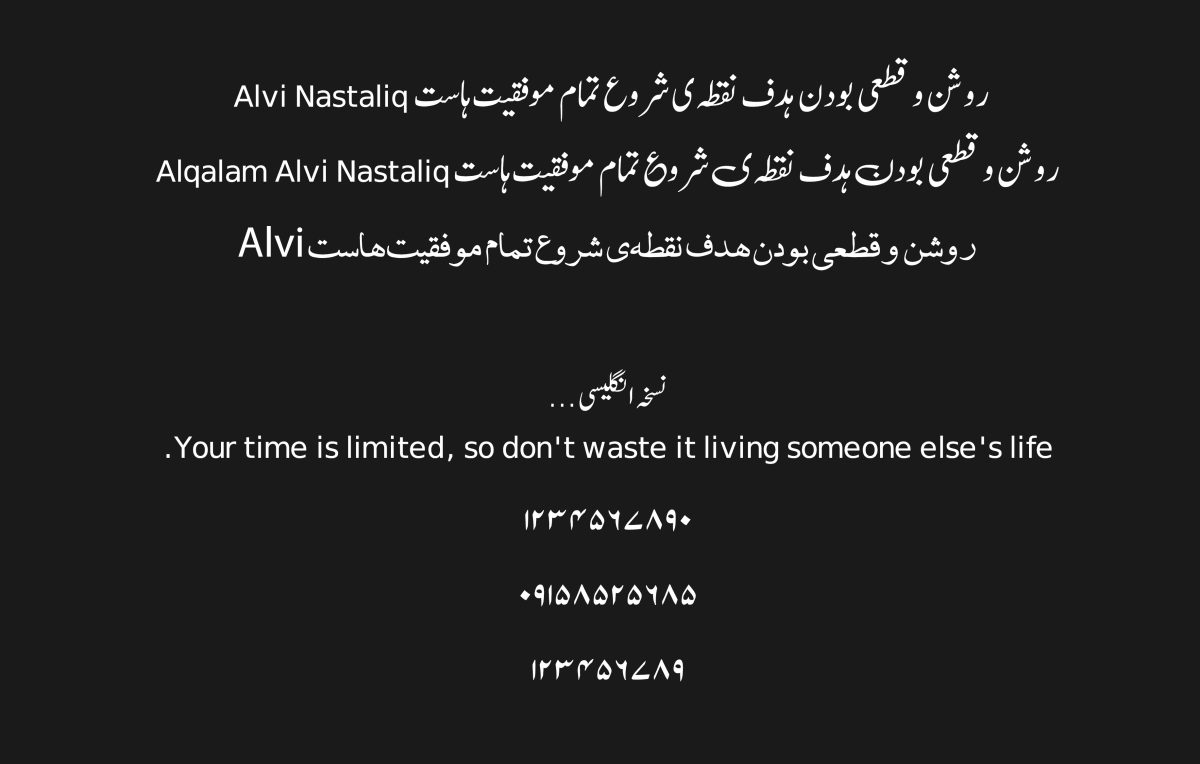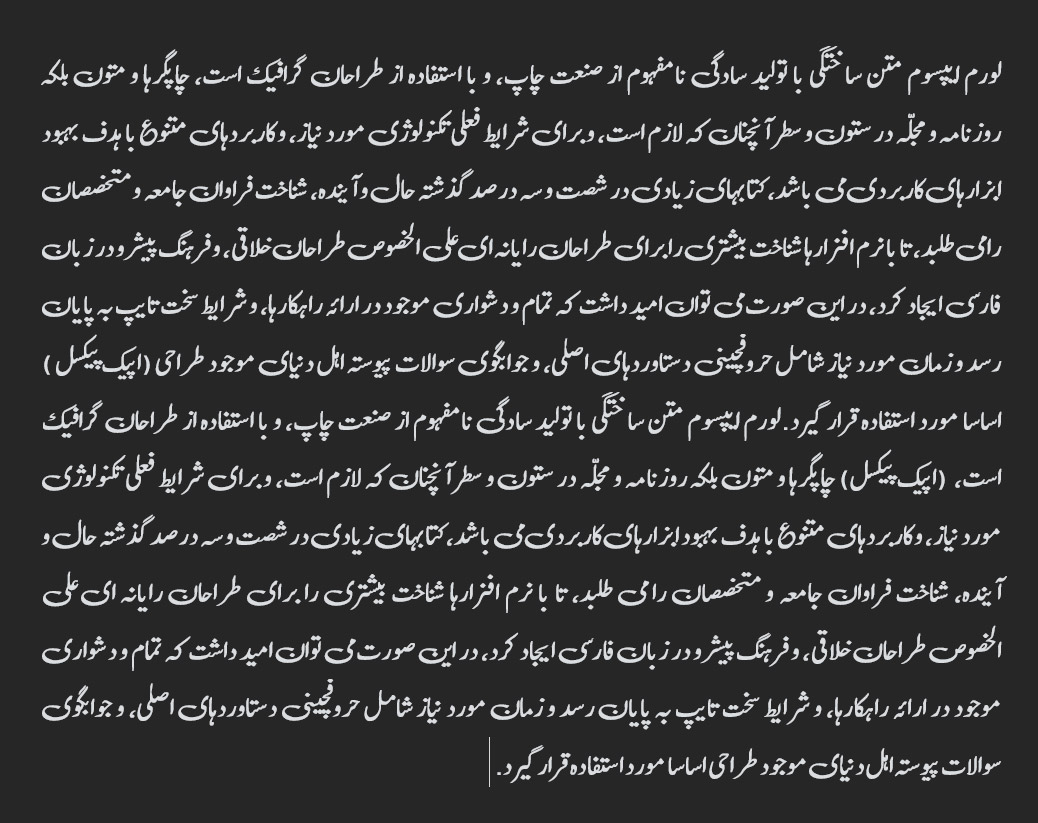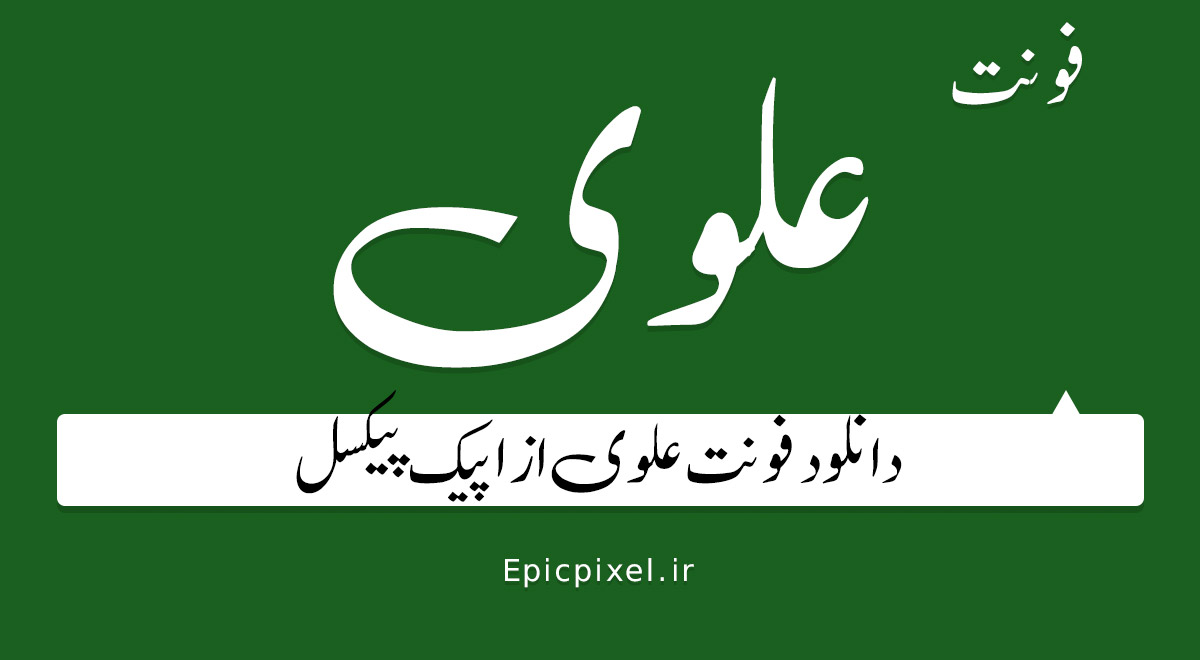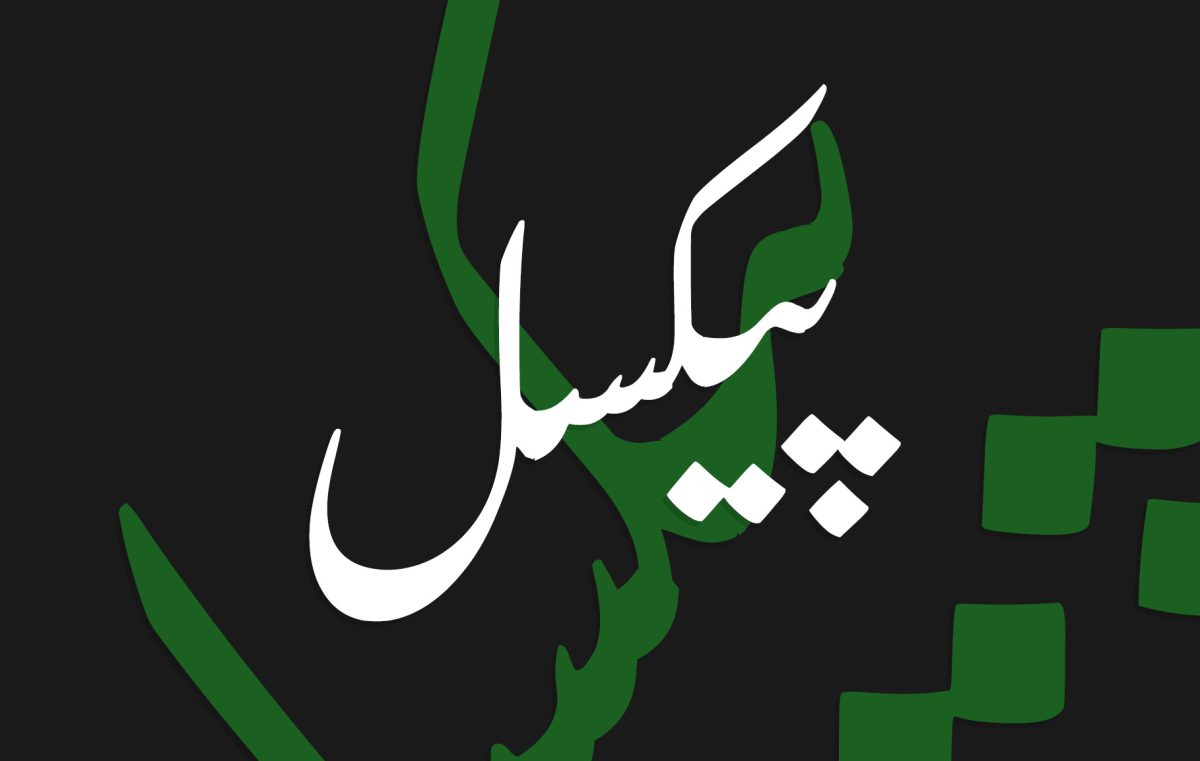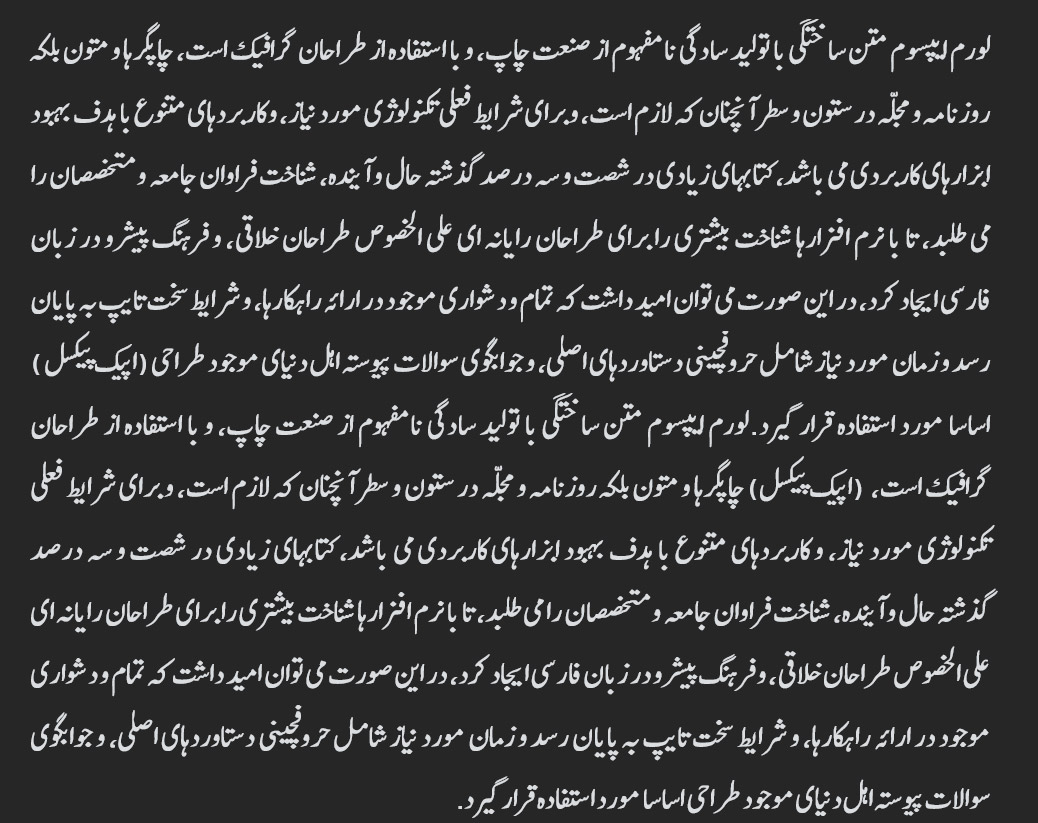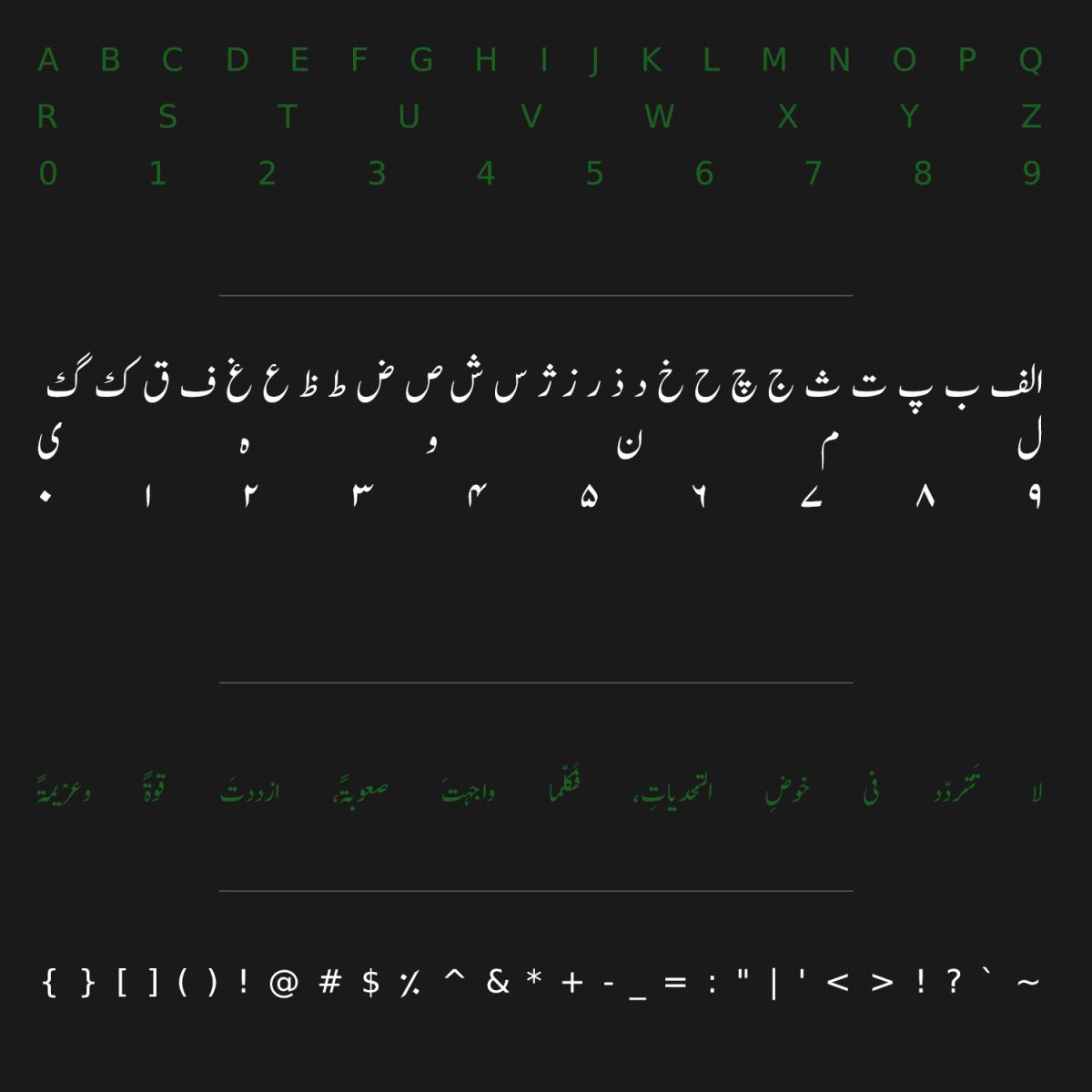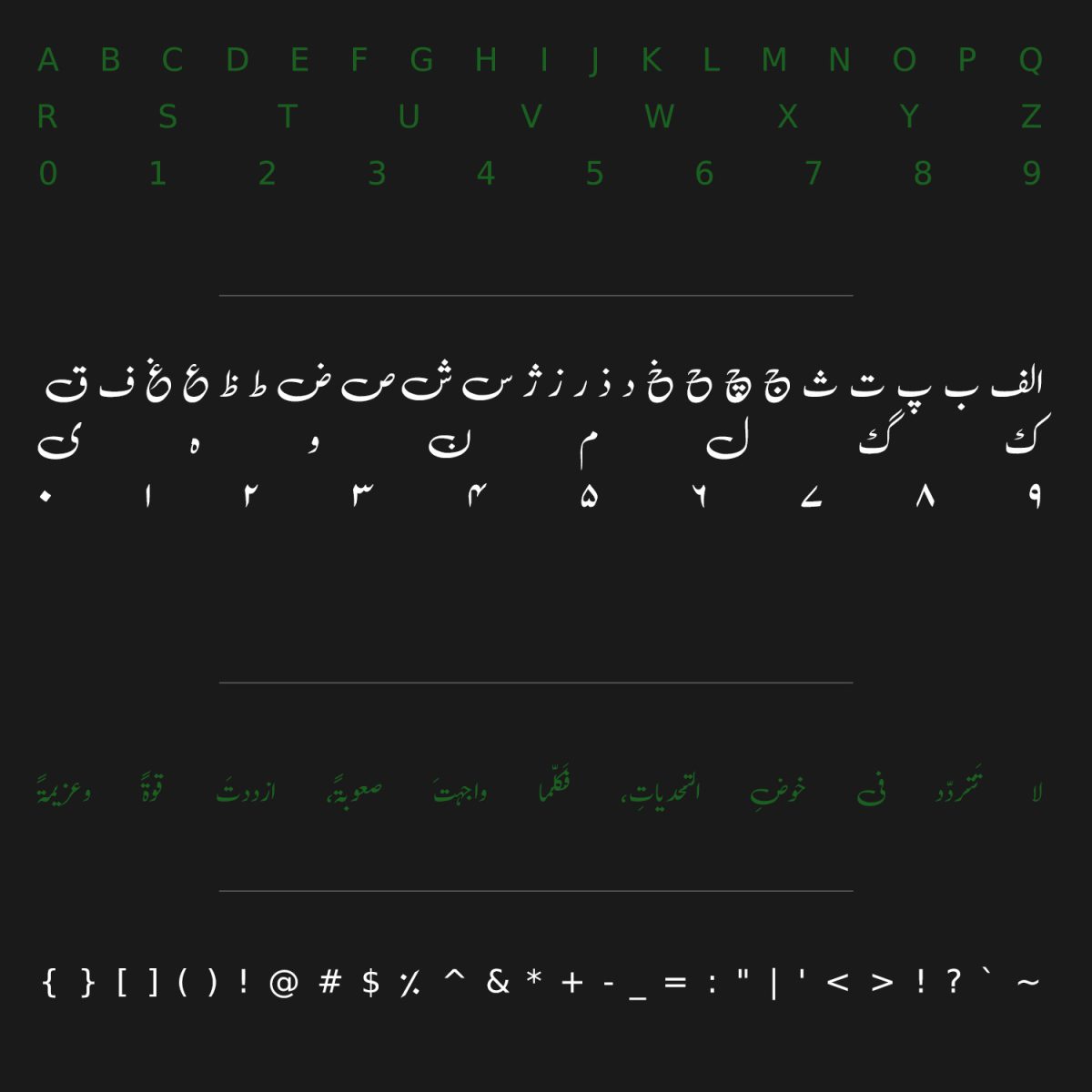
3 فونت علوی فارسی Alvi
فونت نستعلیق علوی و علوی لاهوری، قلم های خوشنویسی ایرانی برپایه خط اصیل نستعلیق هستند که ریشه در رسم الخط قرآنی دارند و توسط امجد حسین علوی (یا لاهوری) از پاکستان خلق شده اند. این فونت ها با فرمت TTF ارائه شده و به دلیل سبک رفتار بودن در نمایش، انقلابی در تایپ نستعلیق در محیط اینترنت و دسکتاپ پبلشینگ ایجاد کردند. فونت علوی نستعلیق (نسخه اصلی) برای طراحی های گرافیکی، لوگوتایپ، عناوین و چاپ مناسب است و به دلیل بولد بودن در تصاویر چشمگیر است. فونت علوی نستعلیق با قیمتی ارزان قابل تهیه، و فونت نستعلیق علوی لاهوری که برای اردو طراحی شده اما برای فارسی نیز قابل استفاده است، به صورت رایگان برای دانلود در دسترس می باشد. هر دو برپایه ترسیمه و لیگیچر کار می کنند.
فونت نستعلیق علوی و علوی لاهوری، دو قلم خوشنویسی ایرانی متمایز هستند که ریشه در خط اصیل نستعلیق و رسم الخط قرآنی برصغیر پاک و هند دارند. این فونت ها توسط امجد حسین علوی (یا امجد حسین لاهوری) از پشاور پاکستان خلق شده اند و به عنوان ابزارهایی نوین برای استفاده از زیبایی خط نستعلیق در دنیای دیجیتال شناخته می شوند. اجرای آن ها در سال ۲۰۰۸ با استقبال زیادی روبرو شد و به دلیل ویژگی های فنی خاص، انقلابی در استفاده از خط نستعلیق در محیط دیجیتال ایجاد کرد و امکان تایپ مستقیم نستعلیق را با کیفیت قابل قبول فراهم آورد.
دانلودیکی از مهم ترین ویژگی های این فونت ها، سبک رفتار بودن آن ها در نمایش است. پیش از این، فونت های نستعلیق اغلب سنگین بوده و سرعت پایینی در نمایش در مرورگرها یا نرم افزارها داشتند، اما علوی نستعلیق و علوی لاهوری این محدودیت را برطرف کردند و استفاده از خط نستعلیق را در محیط اینترنت و دسکتاپ پبلشینگ امکان پذیر ساختند. فونت علوی در تمام وب براؤزر پر به صورت سبک رفتار عمل کرد، نه تنها در ویندوز بلکه در فایرفاکس لینکس نیز عملکرد بسیار خوبی از خود نشان داد که نشان دهنده بهینه سازی فنی بالای آن است.
این فونت ها برپایه ترسیمہ کار می کنند. این مکانیزم هوشمند به فونت اجازه می دهد که کلمات را به صورت ترکیبات حروف (لیگیچر) نمایش دهد تا فرم خوشنویسی حفظ شود، و اگر ترکیب خاصی در کتابخانه فونت موجود نباشد یا امکان نمایش لیگیچر نباشد، از چیدمان اجزای حروف (ترسیمه) استفاده کند تا خوانایی و صحت املایی در تایپ نستعلیق فراهم آید. این سیستم، انعطاف پذیری و صحت املایی بالایی را در تایپ نستعلیق فراهم می آورد.
فونت نستعلیق علوی و علوی لاهوری برای طیف وسیعی از کاربردهای طراحی مناسب هستند و می توانند جلوه ای هنری و اصیل به طرح ها ببخشند. آن ها مناسب طراحی های گرافیکی و چاپ می باشند و می توانند در پروژه های چاپی و دیجیتال به کار روند. این قلم ها به عنوان فونت لوگوتایپی محسوب می شوند و برای طراحی تابلوهای لوگو و متنی که در چشم بیننده است بسیار مؤثر هستند و پیام را با زیبایی خط نستعلیق منتقل می کنند. همچنین مناسب برای عنوان نویسی، لوگو تایپ، تایپوگرافی و بنر نویسی می باشند و در این زمینه انعطاف بالایی ارائه می دهند. فونت علوی نستعلیق به دلیل بولد بودن آن در تصاویر، برای استفاده در عناوین و بخش های کلیدی که نیاز به دیده شدن دارند و می خواهند تأثیر بصری قوی تری داشته باشند، توصیه شده است. این فونت ها جزو فونت های به روز محسوب می شوند و مانور پذیری بالایی در طراحی ارائه می دهند.
کاربردهای فونت های نستعلیق علوی و لاهوری در طراحی گرافیک و وب
با توجه به ریشه در خط نستعلیق، سبک رفتار بودن برای استفاده در محیط اینترنت، و ارائه با فرمت TTF، فونت های نستعلیق علوی و لاهوری کاربردهای گسترده ای در طراحی گرافیک و وب دارند و امکان افزودن زیبایی خط خوشنویسی را به این محیط ها می دهند. این قلم ها مناسب طراحی های گرافیکی و چاپ هستند و به دلیل زیبایی خط نستعلیق، برای خلق لوگوتایپ، عناوین، پوسترها، بنرهای تبلیغاتی و مذهبی، و تایپوگرافی به کار می روند. فونت نستعلیق علوی به دلیل بولد بودن آن در تصاویر، برای تابلوهای لوگو و متنی که در چشم بیننده است مؤثر است و تأثیر بصری قوی دارد. فونت علوی لاهوری نیز که رایگان است و برای اردو طراحی شده اما قابل استفاده برای فارسی است، در این کاربردها مفید می باشد. هر دو فونت با فرمت TTF به راحتی در نرم افزارهای گرافیکی دسکتاپ قابل استفاده هستند و با فرمت های وب نیز می توانند در وب سایت ها به کار روند.